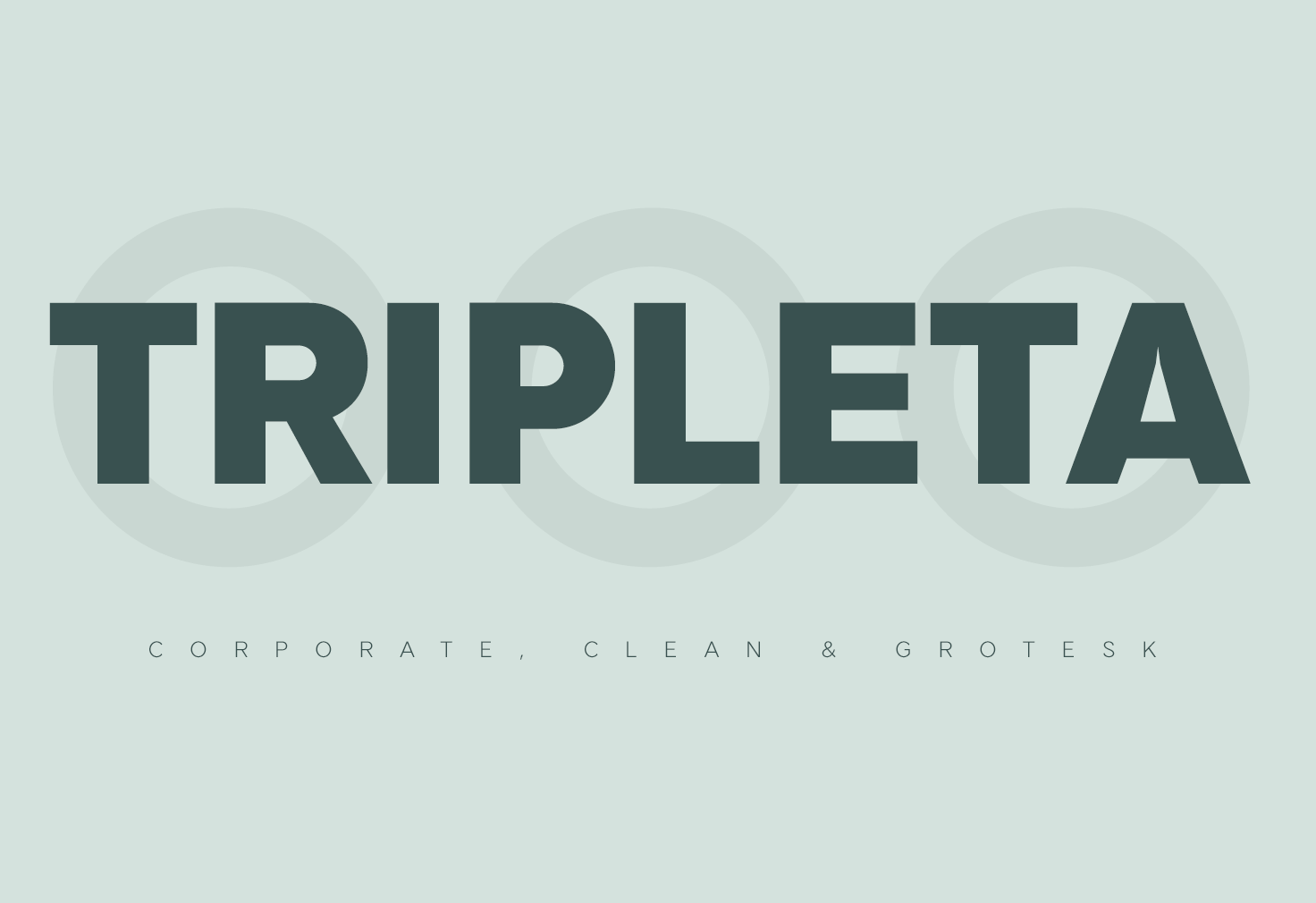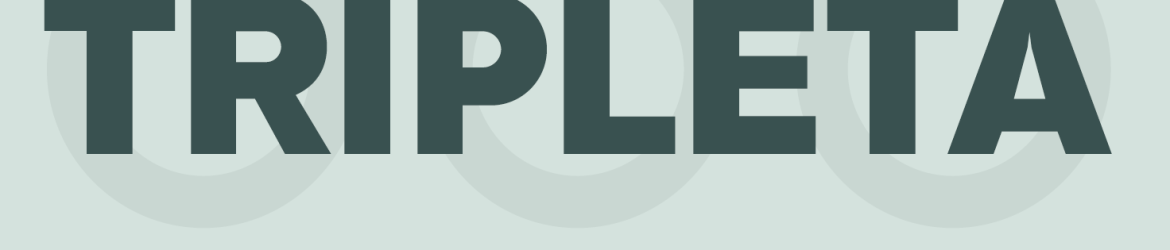
A Tripleta Grotesk é uma família tipográfica composta por 16 tipos diferentes, projetada para transmitir uma aparência limpa e profissional. Básica na sua construção geométrica, a letra reflete os conceitos de projeção tridimensional que estabeleci com cuidado, focando nos três eixos fundamentais. Cada caracter é meticulosamente detalhado para garantir uma combinação harmônica entre espaçamento (kerning) e configuração, criando um equilíbrio perfeito para a leitura. Além disso, os versos em itálico apresentam suas próprias letras minúsculas estilizadas com uma inclinação de 13 graus. Tudo isso é complementado por funções avançadas do OpenType e pelo símbolo do Bitcoin (b#). Esta fonte não apenas adiciona um toque elegante a qualquer projeto, mas também oferece flexibilidade para personalização única. A Tripleta Grotesk foi projetada com o designer defharo, conhecido por suas criações de tipo modernas e claramente funcionais. Para quem busca uma fonte minimalista e funcional, esta família tipográfica pode ser um excelente complemento à sua biblioteca de fonts.